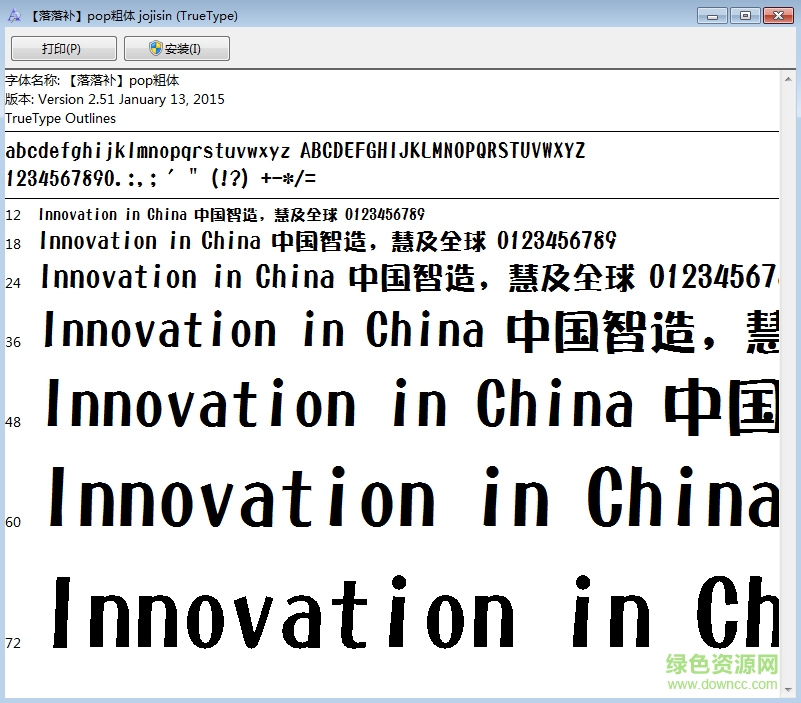
pop粗體是一款明顯加粗的的藝術(shù)字體,更顯端正大方,適用于引導(dǎo)消費(fèi)、活躍氣氛等場合,喜歡的朋友快來綠色資源網(wǎng)下載吧!
pop粗體是落落補(bǔ)創(chuàng)作的中文字體,字體端正大方,格式嚴(yán)謹(jǐn),被廣告設(shè)計(jì)、印刷彩印、文字排版等行業(yè)人士使用,商務(wù)使用需到官網(wǎng)授權(quán)哦!